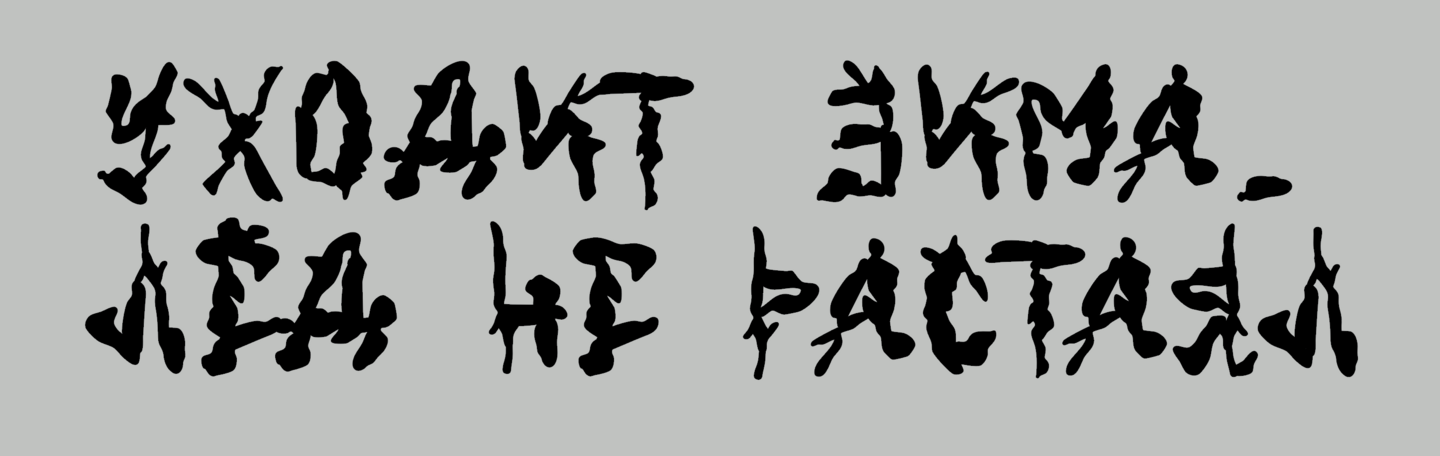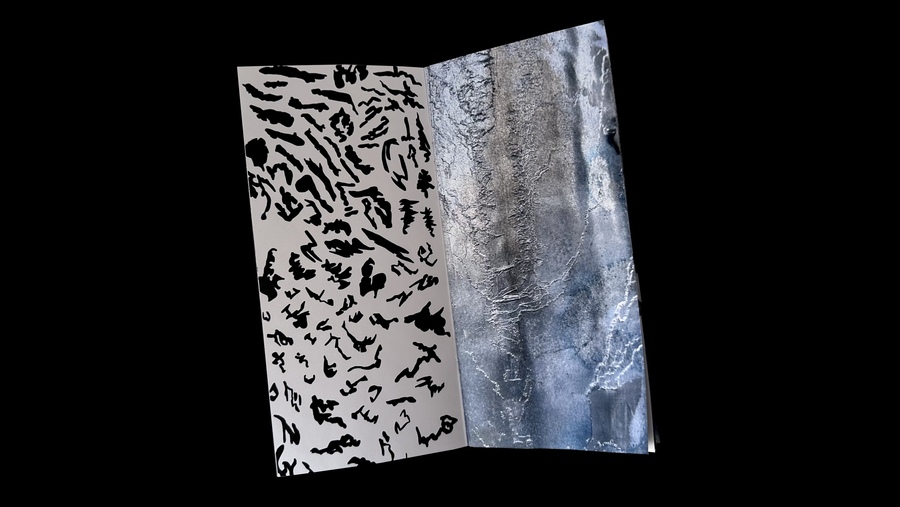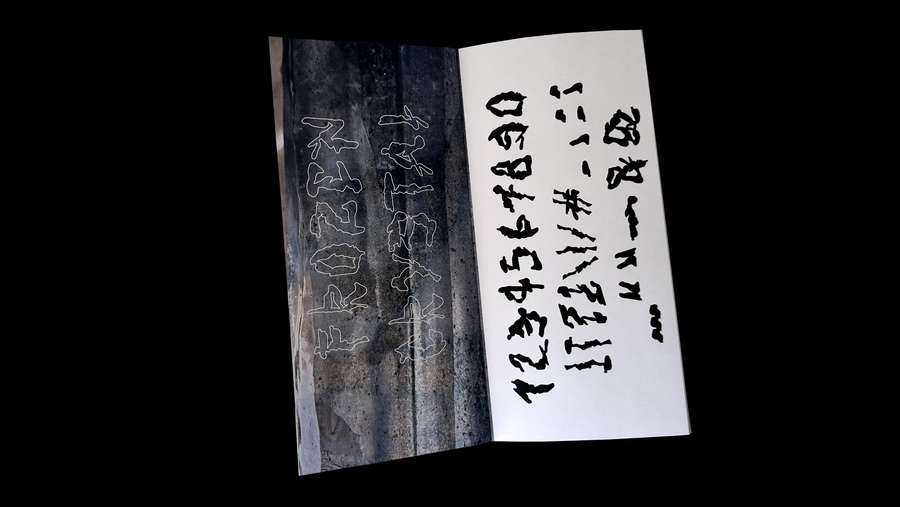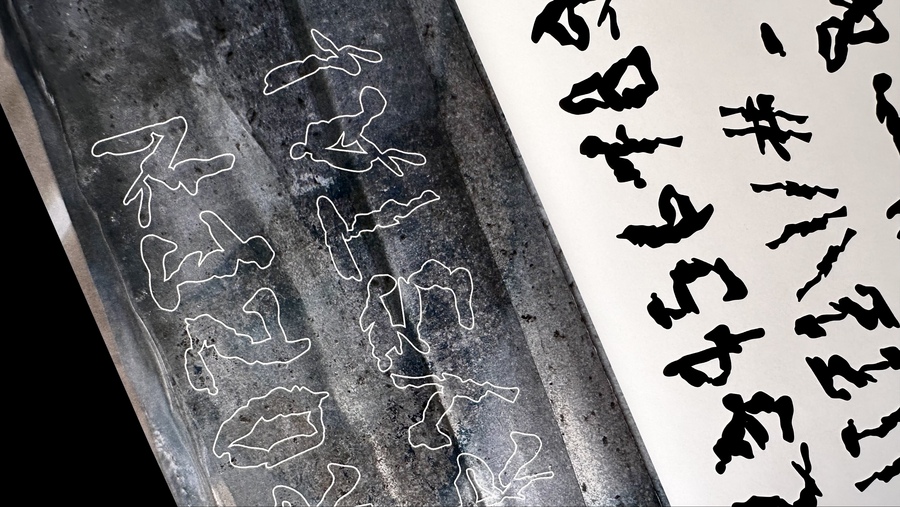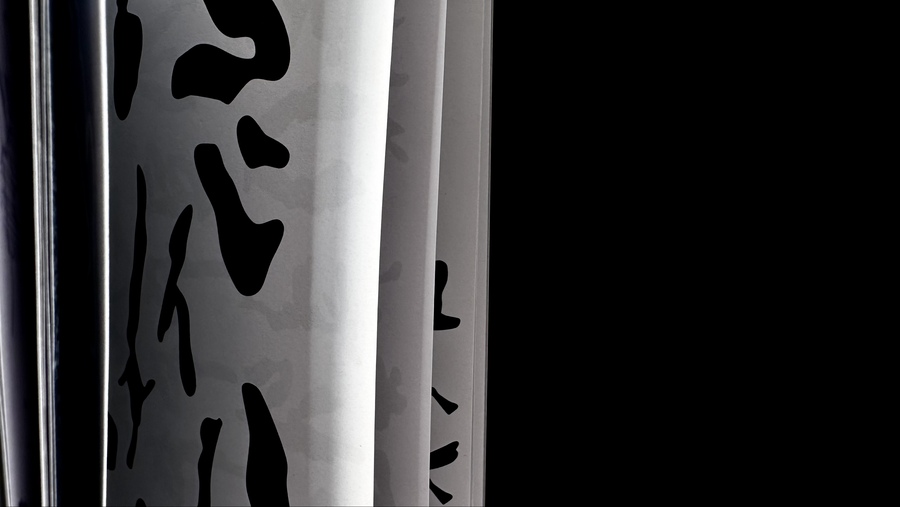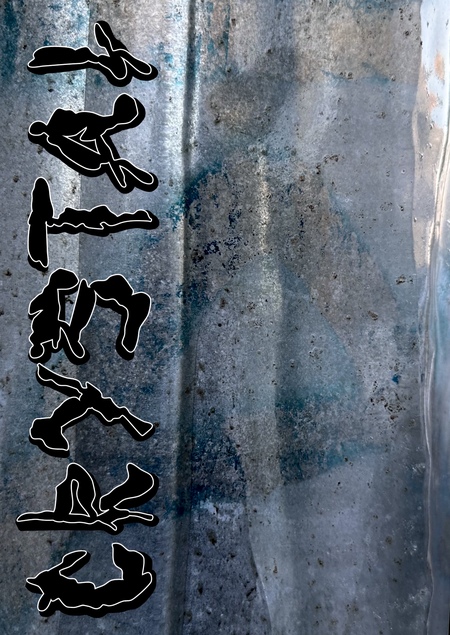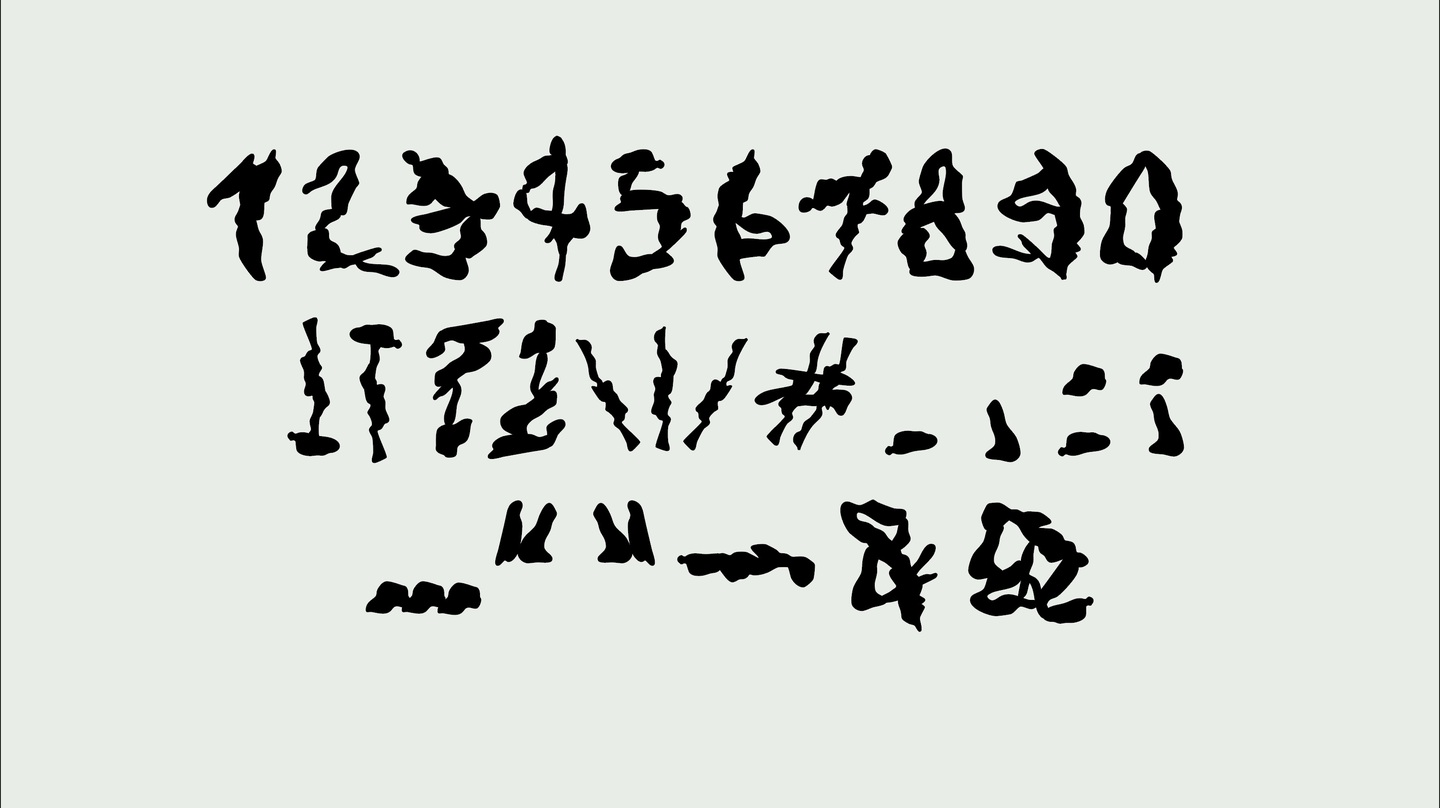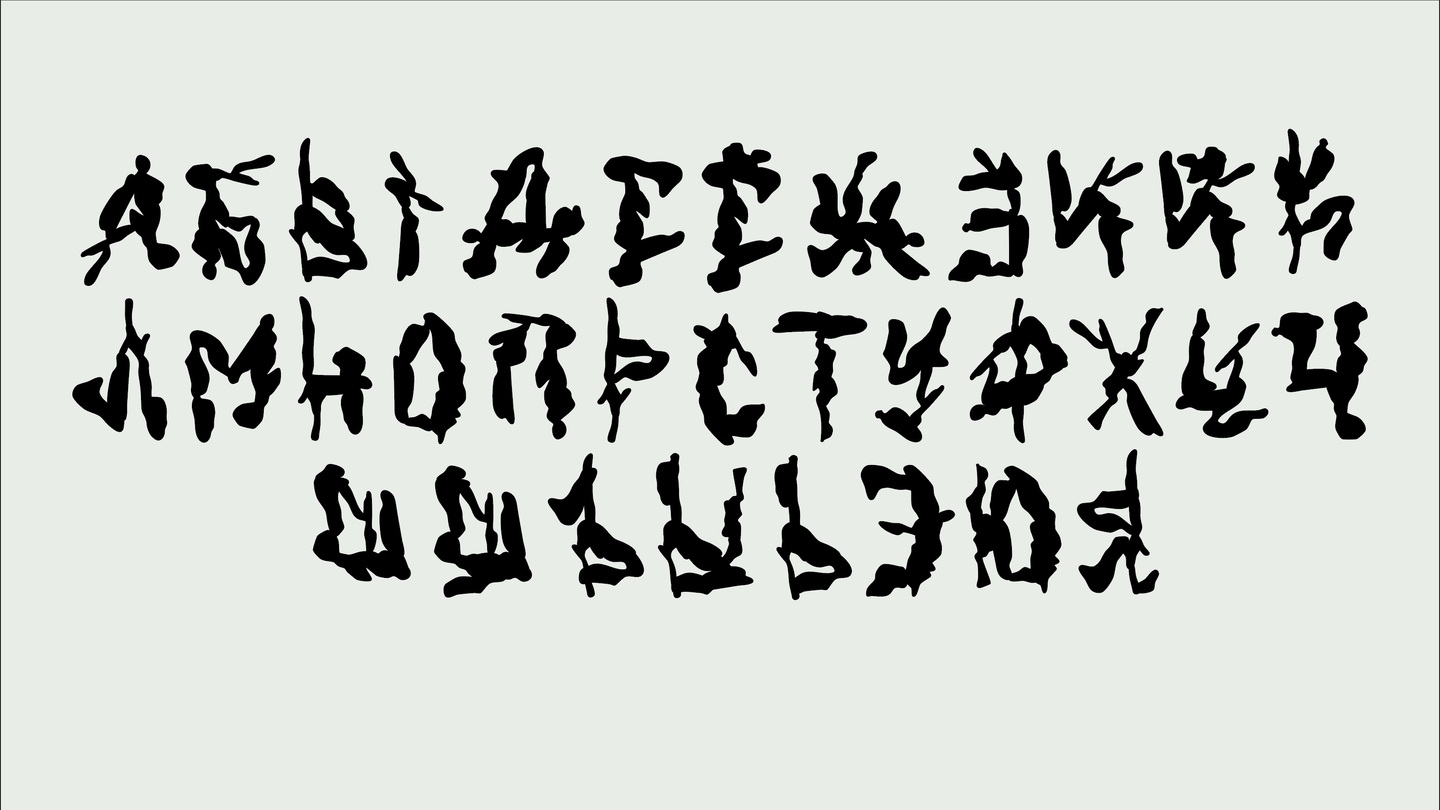
Это модульный шрифт, созданный на основе форм льда в городской среде. Шрифт подражает застывшей нерукотворности в попытке уловить ритмичность того, что сперва кажется хаотичным.
ICE CRYSTAL REGULAR
ICE CRYSTAL OUTLINE
уходит зима. а лед не растаял